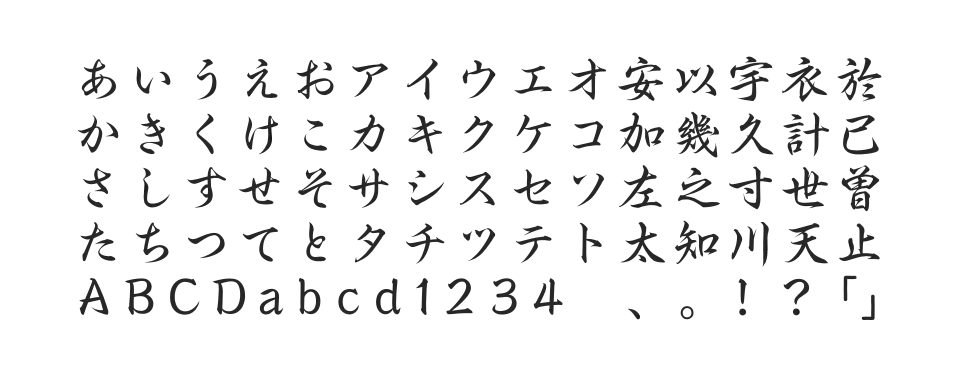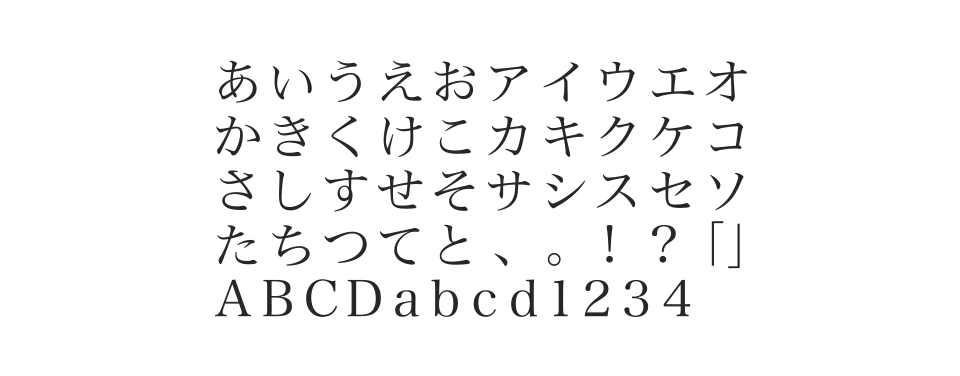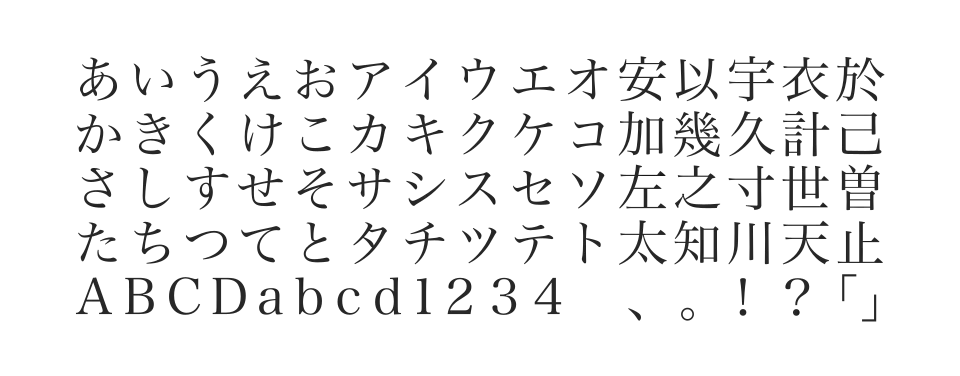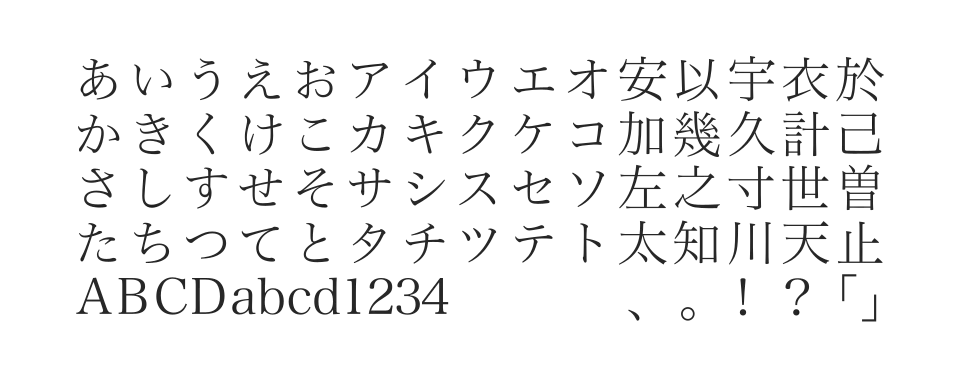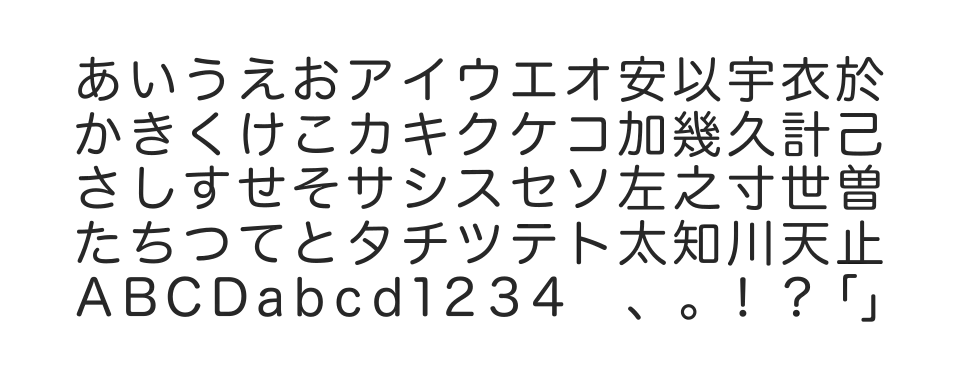
ヒラギノシリーズの丸ゴシック体。シャープでモダンな印象を継承しつつ、自然な柔らかみとあたたかさを持った洗練された書体。本文にも見出しにも使用可能。
現代的でシャープな表情の中に伝統的な筆文字の美しさをマッチさせた明朝体。最大規模の文字セットで令和合字やIVSにも対応した最上位仕様。
現代的でシャープな表情の中に伝統的な筆文字の美しさをマッチさせた明朝体。豊富な文字セットで人名や学術用語にも対応。JIS90字形対応版。
現代的でシャープな表情の中に伝統的な筆文字の美しさをマッチさせた明朝体。豊富な文字セットで人名や学術用語にも対応。JIS2004字形対応版。
現代的でシャープな表情の中に伝統的な筆文字の美しさをマッチさせた明朝体。フトコロを広めに、重心を軽やかに高めたデザイン。JIS90字形対応版。
現代的でシャープな表情の中に伝統的な筆文字の美しさをマッチさせた明朝体。フトコロを広めに、重心を軽やかに高めたデザイン。JIS2004字形対応版。
共同通信社が新聞報道用に定めたU-PRESS文字セットに対応した明朝体。新聞・報道業界で使用される特殊文字や記号を収録し、報道用途に最適化されたフォント。
ヒラギノ明朝のデザインに合わせた横組み専用かな書体。ベタ送りの組版でも字間に疎密が少なく、美しくラインが揃うようにデザインされた横組み専用書体。
毛筆特有の豊かな量感をデジタルフォントで再現した行書体。緩急自在の運びで印刷用見出しから石碑・表札まで幅広いシーンに対応。JIS90字形対応版。
毛筆特有の豊かな量感をデジタルフォントで再現した行書体。緩急自在の運びで印刷用見出しから石碑・表札まで幅広いシーンに対応。JIS2004字形対応版。